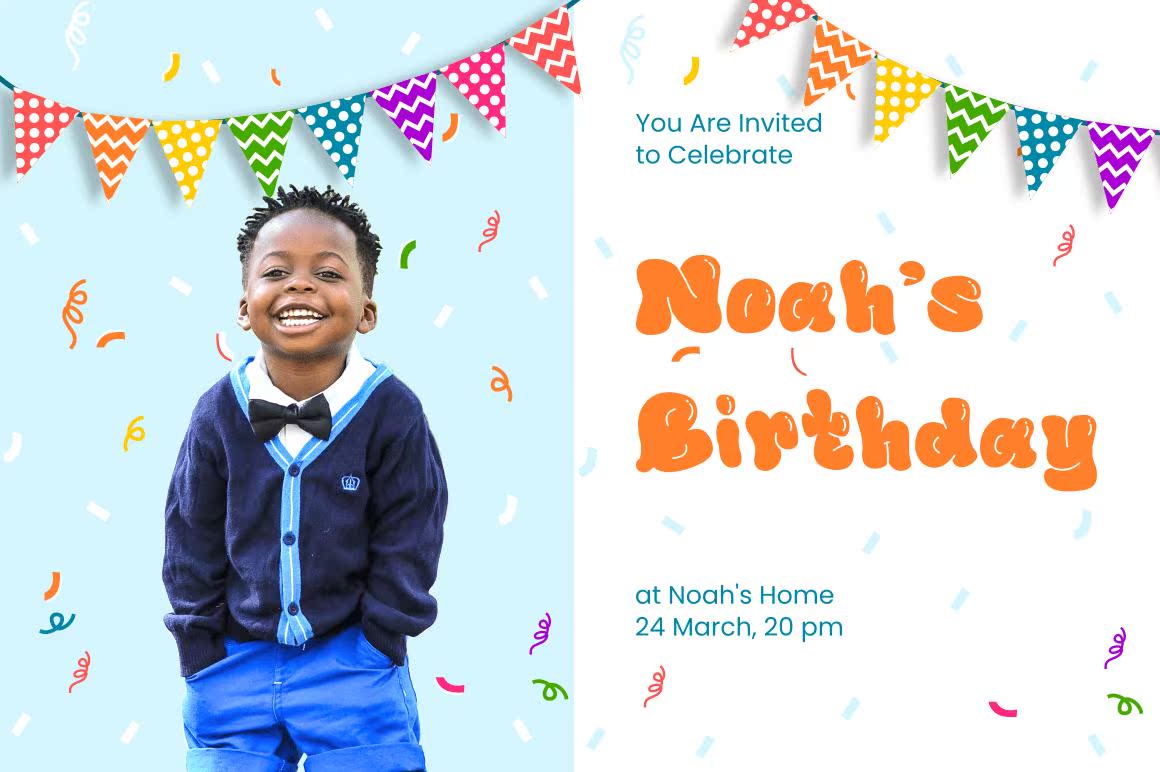
Gembila字体是剪切和未显示的字体。ItemBody显示完整性和身份验证,并区分所有儿童活动或学校项目的完美选择。将此Chunkylettered字体添加到您的设计中,并注意它如何使MCome处于活动状态!GembilaFont包括完整的设置PerCase和小写字母、数字和符号。Gembila Font是剪切和未显示的Font.ItemBody可显示性和验证性,并可区分所有儿童活动或选择项目的完整选项。将此ChunkyletteredFont添加到您的设计中,并注意它如何使MCome处于活动状态!GembilaFont包括完整设置PerCase和小写字母、数字和符号。